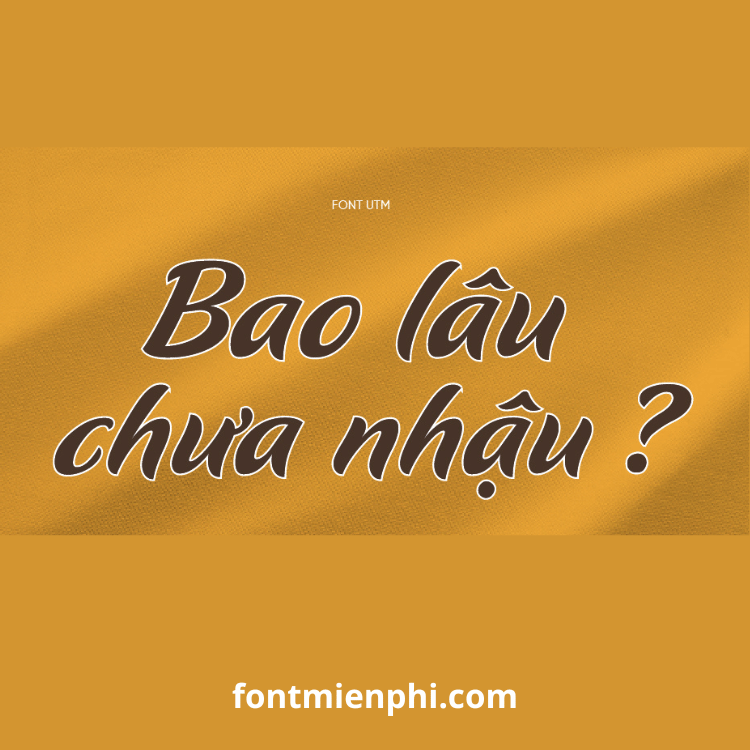
Font Việt hóa UTM Flavour
Mô Tả Chi Tiết Font Việt Hóa “UTM Flavour”
1. Giới Thiệu Font Việt hóa UTM Flavour
UTM Flavour là một trong những font chữ handwriting (viết tay) đẹp và được ưa chuộng nhất trong cộng đồng thiết kế Việt Nam. Font mang phong cách mềm mại, thanh lịch, với nét chữ tự nhiên như viết tay, phù hợp cho các thiết kế thời trang, mỹ phẩm, thiệp mời, blog cá nhân và branding sang trọng.
2. Đặc Điểm Nổi Bật
✔ Phong cách chữ viết tay tinh tế: Nét chữ mảnh, uốn lượn nhẹ nhàng, tạo cảm giác gần gũi và cá tính.
✔ Hỗ trợ đầy đủ Tiếng Việt: Bao gồm đầy đủ dấu và ký tự Unicode, tương thích với mọi phần mềm (Photoshop, Illustrator, Word, Canva…).
✔ Đa dạng ký tự: Hỗ trợ chữ hoa, chữ thường, số và một số ký tự đặc biệt.
✔ Dễ kết hợp: Font phù hợp với các thiết kế cần sự nhẹ nhàng, nữ tính hoặc phong cách tối giản.
3. Ứng Dụng Phổ Biến
• Thiết kế thời trang & mỹ phẩm (logo, poster, bao bì).
• Thiệp cưới, thiệp mời, lời chúc.
• Blog cá nhân, quote, content mạng xã hội.
• Nhận diện thương hiệu cửa hàng café, tiệm bánh.